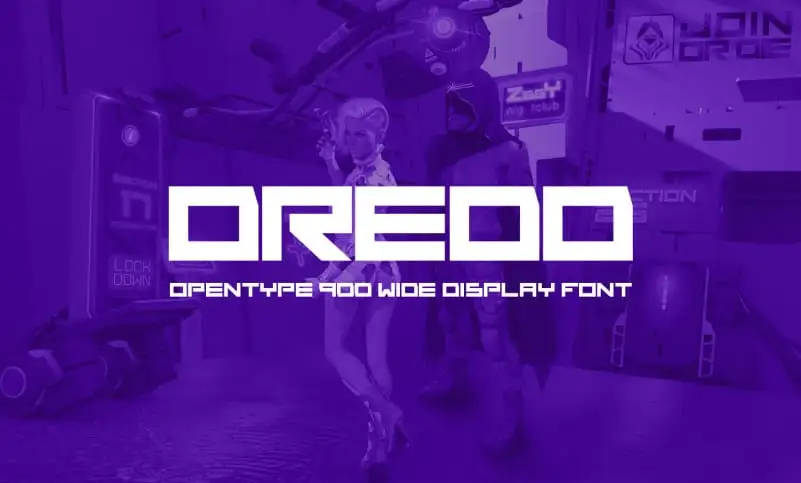
Dredd Display Font – Download Grátis
A Dredd Display Font é uma elegante escolha para projetos que exigem destaque, criando um forte impacto visível através do seu estilo bold e reto. Criada pelo designer Koray Öztürk, essa fonte exibe os caracteres em largura acentuada, oferecendo um olhar retrofuturista perfeito para ambientes de marketing e redação. Suas formas robustas e seus elementos alternativos permitem uma ampla gama de aplicabilidades que vão além da simples escrita, permitindo-a se adaptar bem a design gráfico de logotipos, banners ou qualquer outro material visual em destaque. A Dredd é perfeita para projetos que valorizam um estilo moderno e forte, combinando elegância com uma roupagem futurista. É a fonte certa quando você precisa de uma maneira única e memorável de destacar seu design.